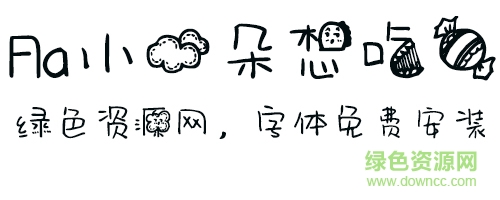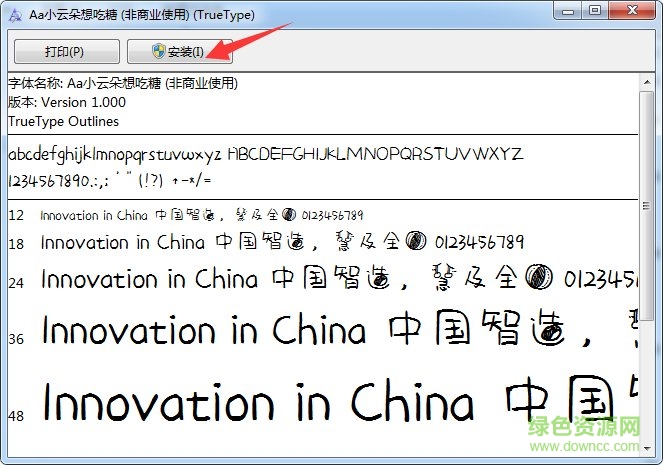
小云朵想吃糖字體是aa字體中的一款免費(fèi)卡通字體文件。繼承了aa字庫系列呆萌有趣的字體風(fēng)格,可以用來設(shè)計一些兒童卡通類宣傳報。小編還為大家提供了詳細(xì)的字體安裝教程,歡迎下載使用。
Aa小云朵想吃糖字體的特別之處在于激昂文字里的每一個糖字都用了大大的糖果代替,看上去就充滿了甜蜜!喜歡這款字體的用戶快來綠色資源網(wǎng)下載使用吧!